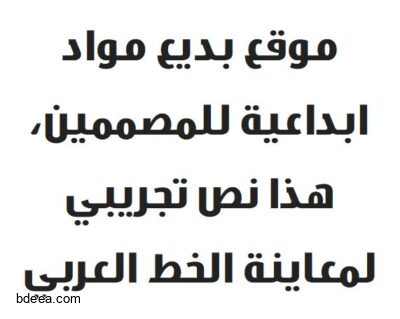
تحميل خط جي ايست شرق GE East ttf font download تضيف نصوص وكلمات عربية بلمسة فنية مميزة الى التصاميم العربية والمطبوعات والعروض التقديمية بالكلمات العربية والارقام بشكل مميز يمكنك تثبيته على جهازك والبدء باستخدامه في برامج التصميم
يتميز بالخط بالمرونة والخفة والشكل الانيق في الكتابة والحروف يمكن معاينته وتجربة استخدامه ليضيف لك تميز الى تصاميمك